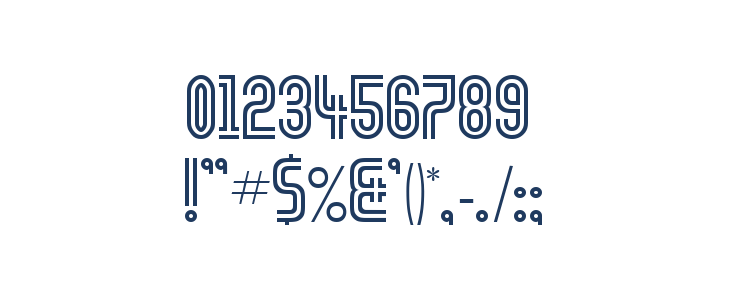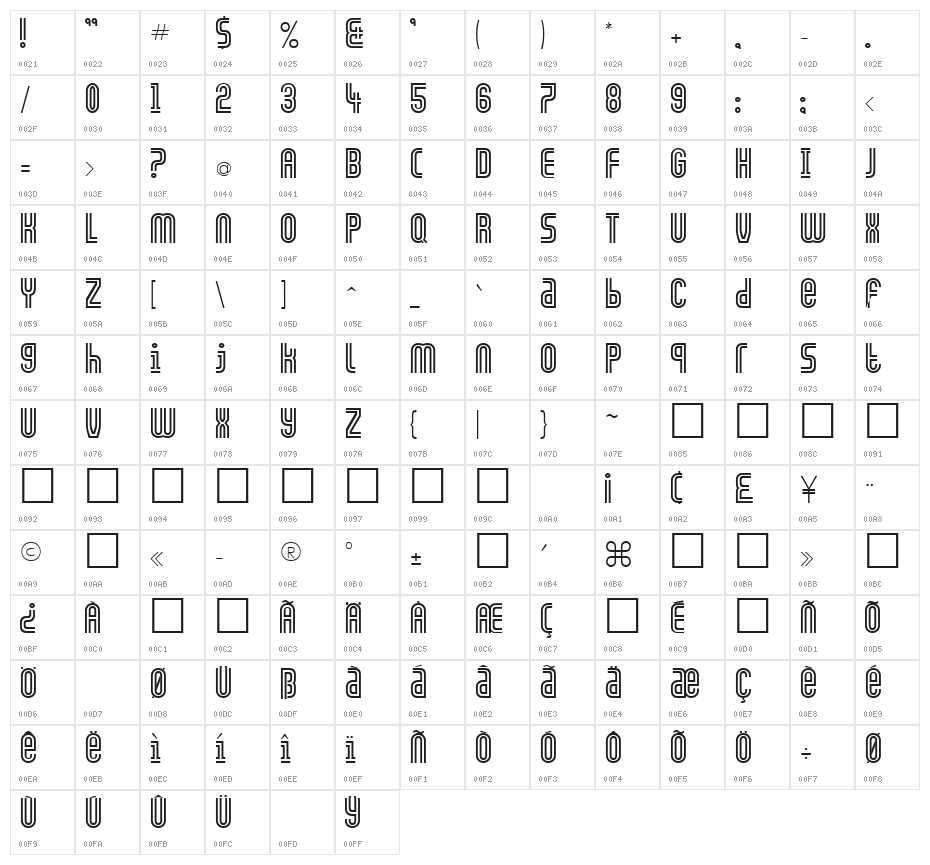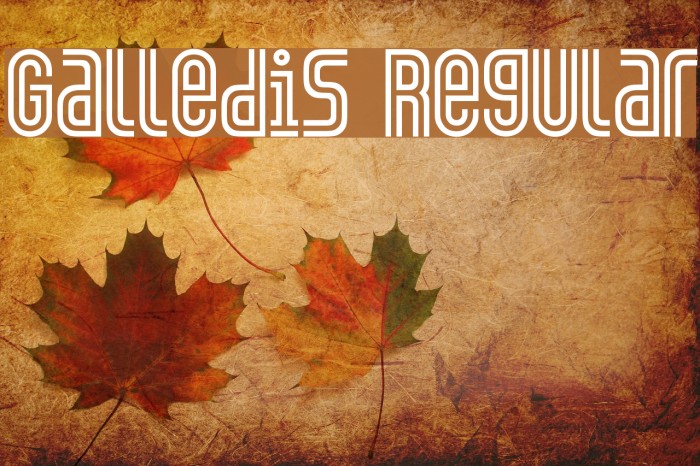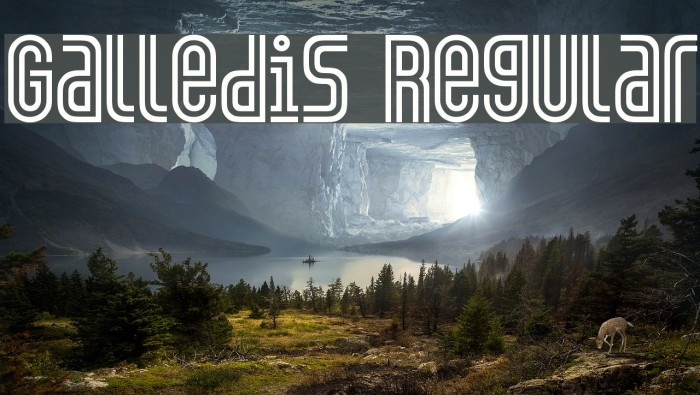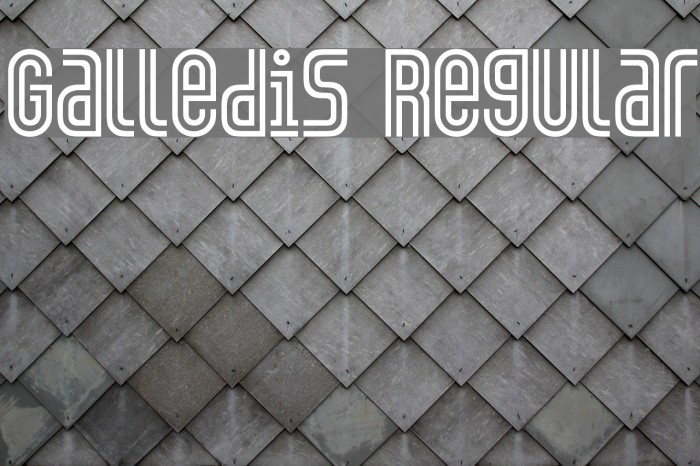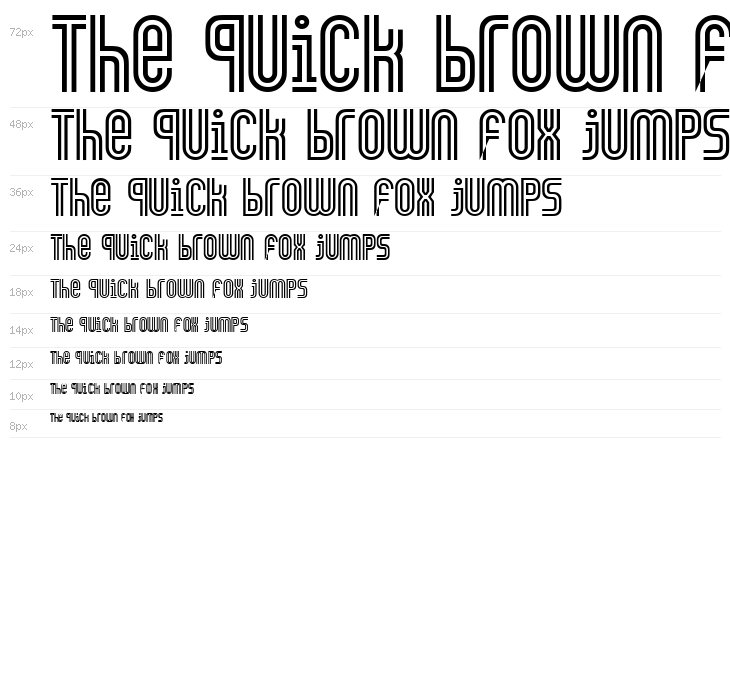
Galledis Regular Font
| Vorgeschlagene Projekte | Ideal for branding, posters, album covers, and any project needing a bold, modern look. |
Galledis Regular